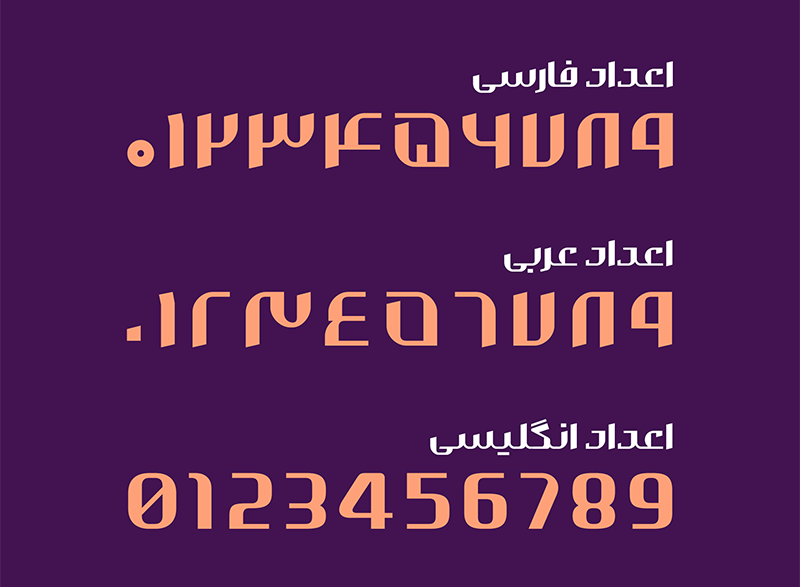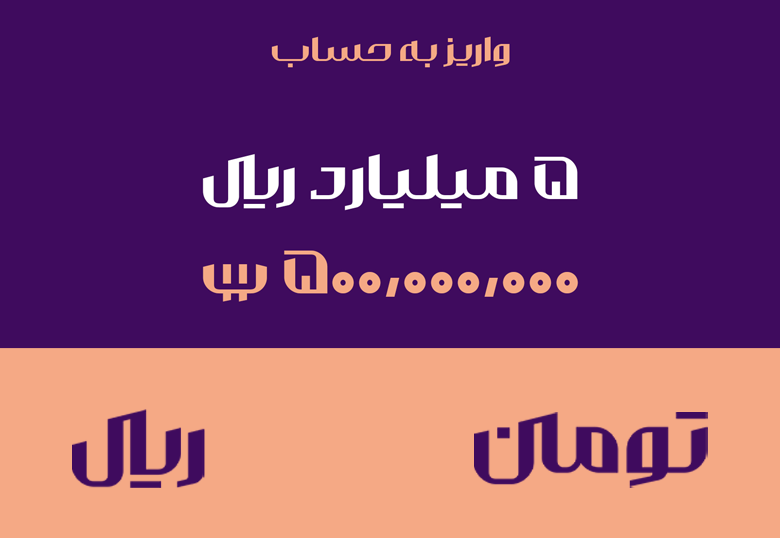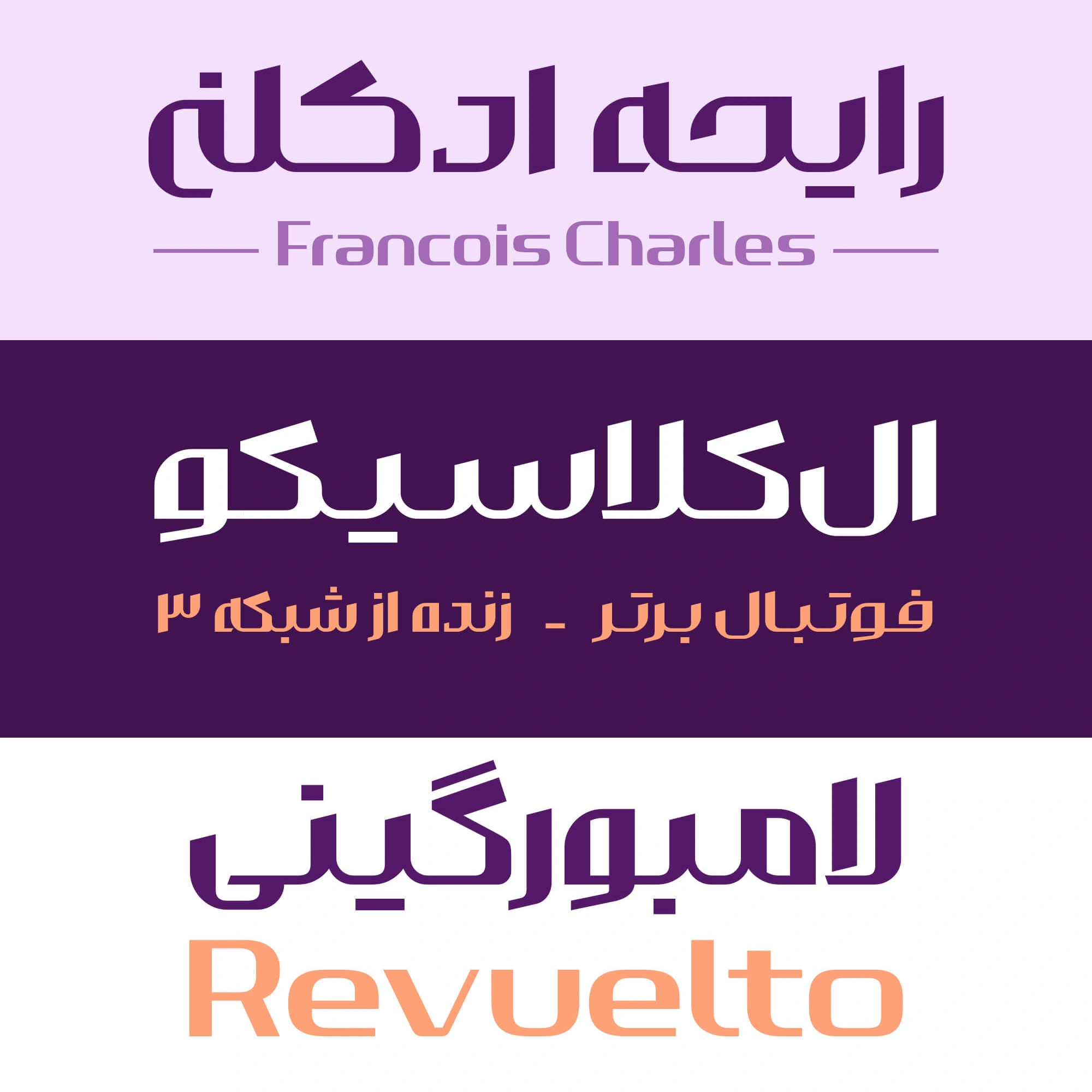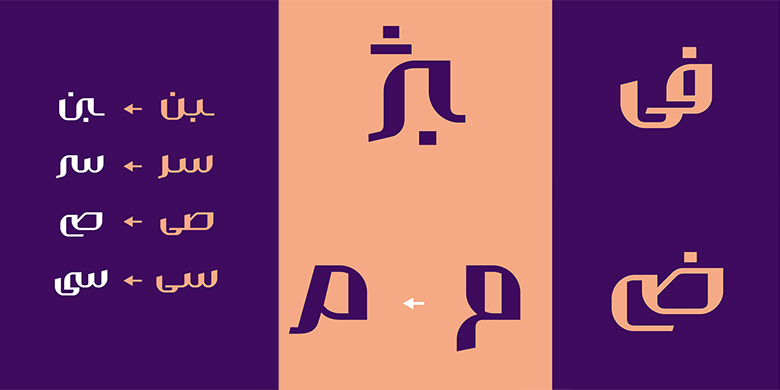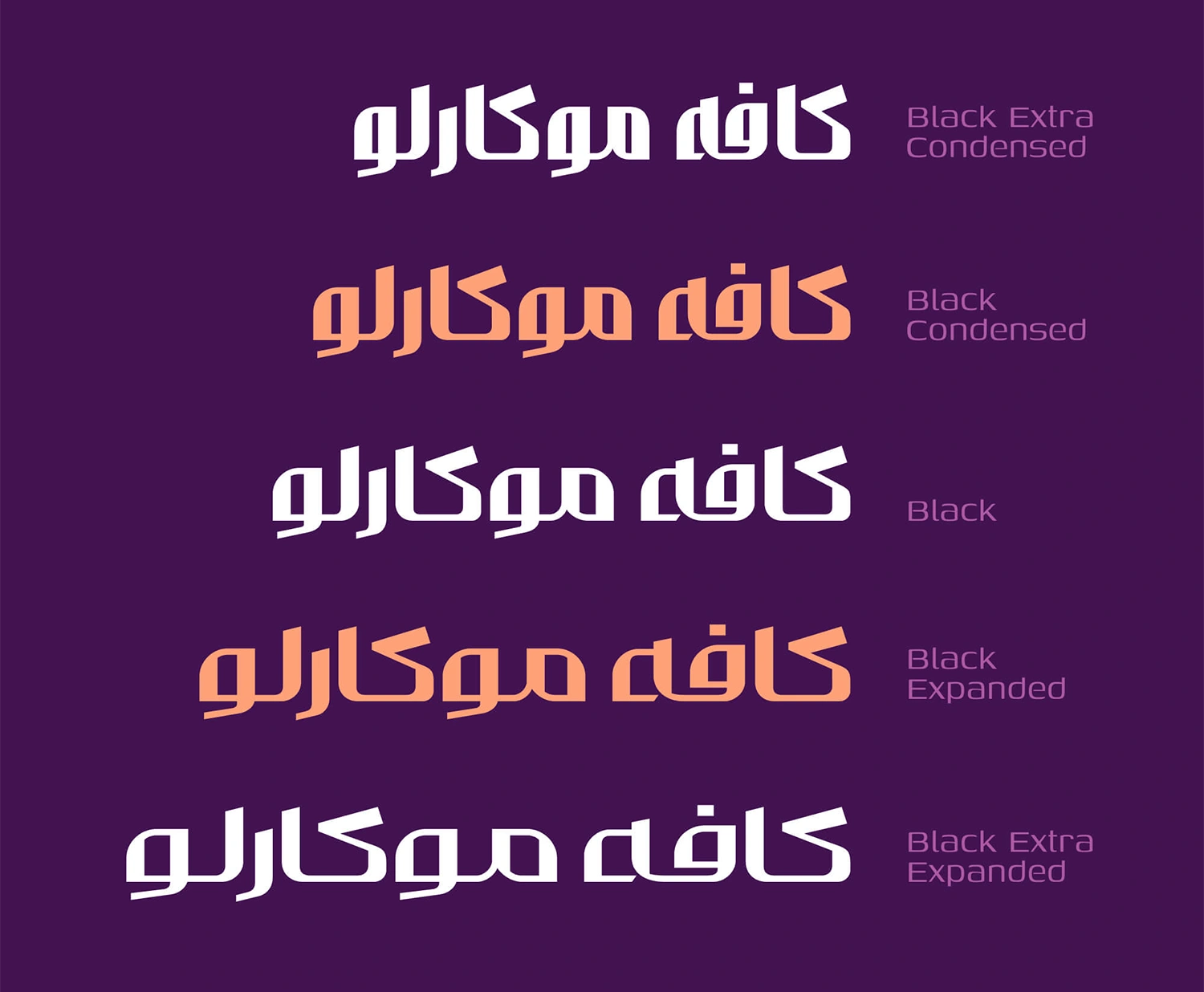
فونت والمان (Valman)
فونت والمان (Valman) توسط حسین حیدری طراحی و توسعه آن را مهدی ارشادی انجام داده است. این فونت در گروه فونتهای عنوان و هندسی است که با ظاهری لوکس، اغما کننده و نمایشی میتواند به هویت بصری برندتان کمک کند. این فونت فارسی با توجه به ساختاری که نزدیک به فونتهای لاتین دارد میتواند برای نوشتههای کپتاه و عناوین انتخاب مناسبی باشد.
فونت والمان فارسی از ۵ وزن ExtraCondensed, Expanded, ExtraExpanded و Black پشتیبانی میکند که میتوانید آن را در سه فرمت TTF برای سیستم عاملها و نرمافزارها و دو فرمت WOFF و WOFF2 برای وب استفاده کنید. علاوهبر این این فونت در بستههایی که برای زبان عربی و فارسی دارای تایپ اعداد مختص همان زبان هستند در دسترس است. در ادامه این نوشته به نقد و بررسی فونت والمان در سایت فونتچی میپردازیم.
معرفی و بررسی فونت والمان (Valman)
اگر بهدنبال یک فونت نمایشی و عنوان هستید که مناسب تبلیغات باشد و تصویری لوکس از برند شما بهنمایش بگذارد، فونت جدید والمان مختص شماست. این فونت دارای شکستگیها و منحنیهای خاصی است که الهام گرفته از فونتهای لاتین هستند.
در طراحی این فونت ارتفاع حروف روند کاهشی دارد که باعث میشود نوشتار فشرده و منظم به نظر برسد. همچنین زاویه قلم و نحوه تقسیم ضخامتها نیز مشابه حروف لاتین است به طوری که راستاهای عمودی ضخیمتر و راستای افقی نازکتر هستند.
در هنگام طراحی یک لوگوتایپ برای برند «هدف دیزاین» نیاز بود لوگوتایپی با ضخامت و کنتراست متفاوت طراحی کنم؛ بههمین دلیل از خطوط عمودی ضخیم و خطوط افقی نازکتر استفاده کردم. در زاویهها نیز برای ایجاد منحنی از دایره استفاده کردم. نتیجه مطلوب بود برای همین پس از مدتی تصمیم گرفتم با هدف طراحی یک فونت حروف آن لوگوتایپ را گسترش دهم.
حسین حیدری؛ طراح فونت والمان
همین ایده باعث شده تا فونت والمان یک کاربرد عالی هم از این نظر داشته باشد و برای طراحی لوگوتایپ گزینه ایدهآلی باشد.
مزایای فونت والمان
مهمترین مزیتی که فونت Valman دارد، طراحی لوکس، مدرن و مناسب برای تبلیغات است. از همینرو میتوان از این فونت برای موارد بسیار متنوعی همچون طراحی لوگو گرفته تا تابلوی فروشگاه و حتی نشانی از برند استفاده کرد.
این فونت امکان پشتیبانی از هر شش زبان فارسی، انگلیسی، عربی، کردی، جاوی و اردو را دارد که در هر یک از زبانها بستههای مختلف این فونت ضمن در دسترس بودن با فرمتهای مختلف، بر اساس اعراب، اعداد و حروف مختص همان زبان در دسترس هستند. بدون اینکه لزومی به تغییر زبان صفحه کلید داشته باشید، میتوانید از اعداد و اعراب همان زبان استفاده کنید. برای زبان لاتین نیز لزومی به تغییر فونت نخواهید داشت.
افزون بر اینها گلیفهای تومان و ریال نیز در این فونت جای گرفته است که میتواند برای استفاده در وب و حتی تبلیغات بنری مورد استفاده قرار گیرد. مهمترین ویژگی این فونت عنوان شاید همین مسئله باشد که با ترکیب کردن آن با یک فونت متن دیگر، بتوانید یک خروجی مناسب از بهنمایش گذاشتن صفحات وب را فراهم کنید.
استفاده از این فونت برای عناوین در وبسایت میتواند تمرکز بیشتر بازدیدکنندگان را به محتوا معطوف کند و از آنجایی که یک ساختار جدید و لوکسی دارد که گلیفهای تومان و ریال را در خود جای داده است؛ میتواند نقش موثری هم روی توجه کاربر به قیمت محصولات و امکان افزایش فروش داشته باشد.
مشخصه دیگر این فونت این است که امکان استفاده از حروف جایگزین را نیز در فرمتهای مختلفی فراهم نموده است. حروفی همچون «ب، س، ص، ی، ک، م و…» در این فونت را در هر بخش از کلمات(ابتدا، میانه و انتها) میتوان در چند ساختار مختلف تایپ کرد.
جدای از این مسئله این فونت در زبانهایی همچون عربی، کردی و اردو که دارای کاراکترهای تزئینی و خاصی هستند دارای اعراب مناسب است. اگر بخواهیم یک جمعبندی کلی از امکانات و ویژگی های این فونت داشته باشیم، عبارتند از:
- فونت عنوان برپایه حروف هندسی و لوکس که دارای ضخامت غیرهمسان بوده، اما در عینحال سعی شده تا در بخشهای مهم حروف ضخامتی با کنتراست بالا حفظ شود.
- امکان پشتیبانی از ۶ زبان مختلف فارسی، عربی، انگلیسی، اردو، کردی و جاوی که در عین حال امکان استفاده از اعداد، اعراب و کاراکترهای تزئینی متناسب با هر فونت در دسترس است.
- دارای یک وزن سنگین سیاه که آن را به فونتی مناسب طراحی لوگو تایپ گرفته تا استفاده از تابلوی فروشگاههای محلی مناسب کرده تا وجههای عالی به برند شما بدهد.
- امکان استفاده از حروف متغیر با شکلهای گوناگون متناسب برای هر زبان. همچون حروف «ک، ی، م، س» که در شکلهای متنوعی در ابتدا، میانه و انتهای کلمات قابل استفاده است.
- پشتیبانی از گلیفهای تومان و ریال که میتواند برای فروشگاههای اینترنتی مناسب بوده و با ایجاد تمرکز بهتر کاربر روی قیمت محصول، یک تاثیر روانی در بازاریابی و افزایش شانس خرید توسط مشتری هم موثر باشد.
- و…
قلم فونت VALMAN دارای طراحی و شکل اختصاصی در حروف خود برای زبان انگلیسی است که از فونت دیگری وامگیری نشده است. همانطور که گفته شد این قلم الهام گرفته شده از طراحی فونت انگلیسی است. لذا در نوشتارها و متون انگلیسی هم میتوانید از ساختار خاص این فونت چه در اعداد و چه حروف بهرهمند شوید.
نسخه وریبل این فونت از تمامی وزنهای پنجگانه پشتیبانی میکند که بدون نیاز نصب نسخههای مختلف میتوانید فقط با نصب این نسخه از همه وزنها استفاده کنید.
طراحی هندسی خاص و عنوانگونه این تایپفیس آن را به گزینهای عالی برای وب تبدیل کرده تا با ترکیب کردن در کنار سایر فونتها بتوان از تاثیری که این فونت روی ذهن کاربر خواهد گذاشت نرخ کلیک روی هر یک از المانهای صفحه وب را بالا برد.